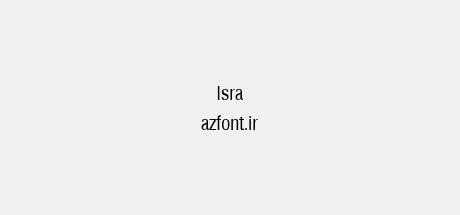
Isra
فونت زیبای رایگان Isra
قلم زیبای Isra Regular از سری قلم های بسیار زیبا برای تایپوگرافی و لوگو تایپ می باشد.این قلم در وزن Regular و توسط Ihsan Al-Hammouri طراحی و منتشر شده است.
Isra, designed by Almamoun Ahmed in 2005, is a modern Kufi and a winner in Linotype's first Arabic Typeface Design Competition. The highly geometric and condensed form make it ideal for magazine headlines, advertising, and general display usage, while the large body height and clear forms make it suitable for short text settings. The font includes a matching Latin design and support for Arabic, Persian, and Urdu. It also includes proportional and tabular numerals for the supported languages.